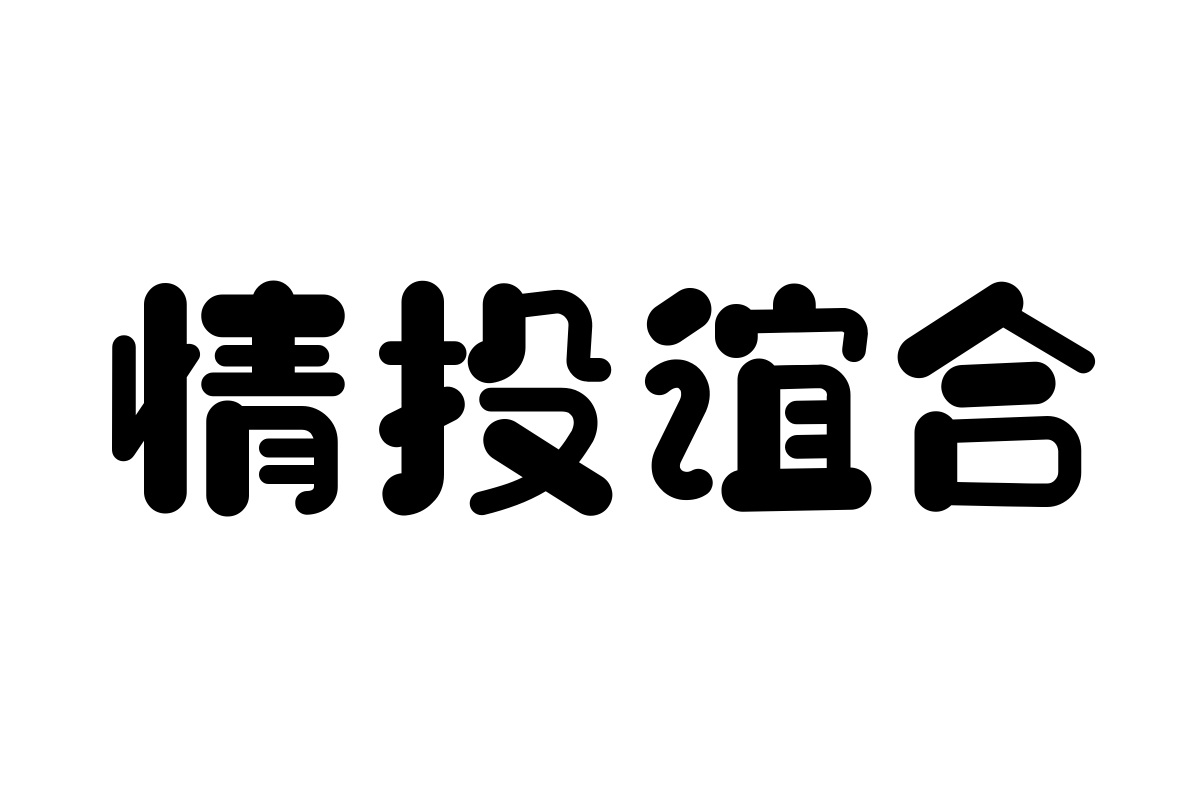
汉仪铸字比心体W是一款由汉仪公司开发的中文字体,具有独特的设计和风格。这款字体采用了比心形状的笔画,给人一种温馨、亲切的感觉,非常适合用于设计海报、宣传册、名片等需要传递情感和氛围的场合。同时,这款字体也适用于各种文字处理软件,如Word、Photoshop、Illustrator等,方便设计师们进行创作和修改。